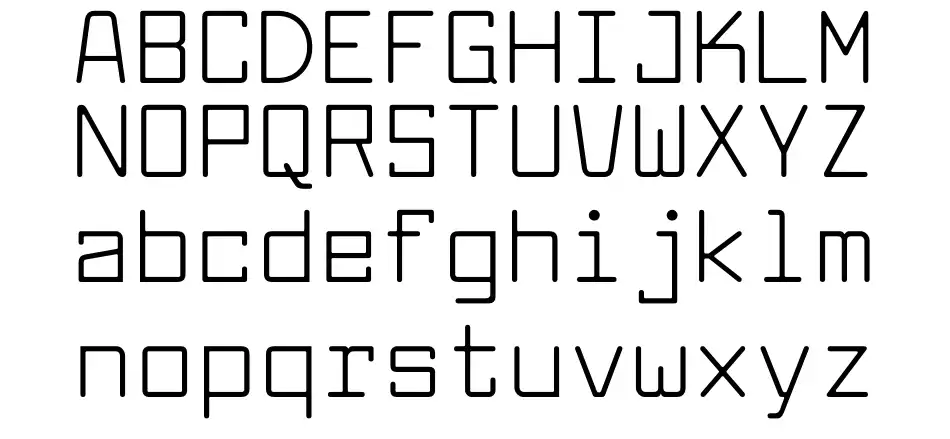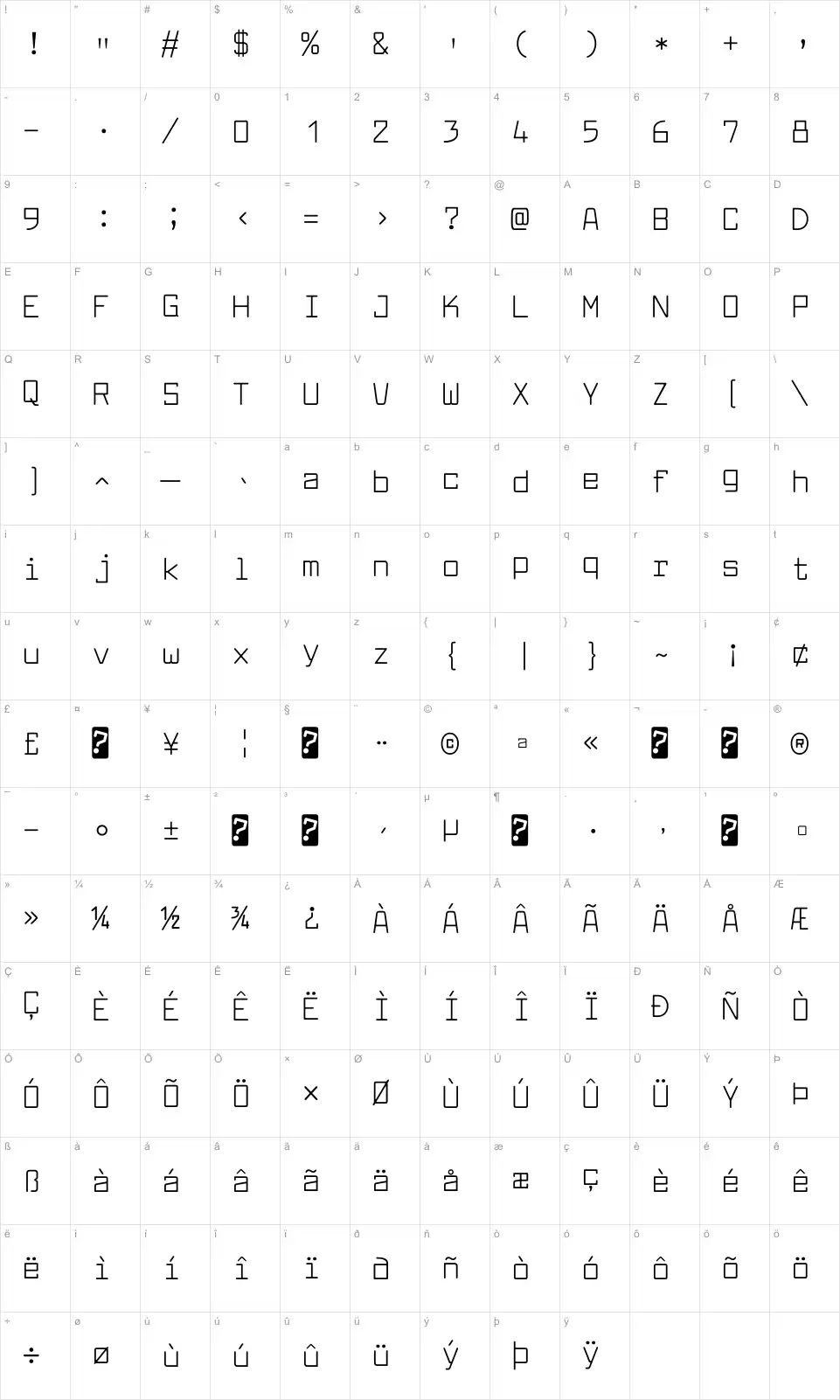
A fonte Larabie Font, criada pela Typodermic Fonts, é uma escolha perfeita para designers que procuram um estilo básico e clean. Com sua categoria fix-width, Larabie Font é ótima para aplicativos, listas de texto e qualquer projeto que exija uma aparência limpa e organizada. Se você está procurando uma fonte para o seu próximo projeto, esta é uma excelente opção. A fonte é gratuita e está disponível em formato TTF. Com apenas 99 KB, ela é levemente maior que a maioria das outras fontes fix-width, mas isso é compensado pela sua facilidade de uso e a capacidade de personalizá-la de forma única. A Typodermic Fonts adicionou a fonte em 11 de julho de 2022, e já foram feitos mais de 2600 downloads. Visite o site da Typodermic Fonts para conhecer melhor a fonte e obter mais informações sobre outras fontes de sua coleção.
Designer: Typodermic Fonts